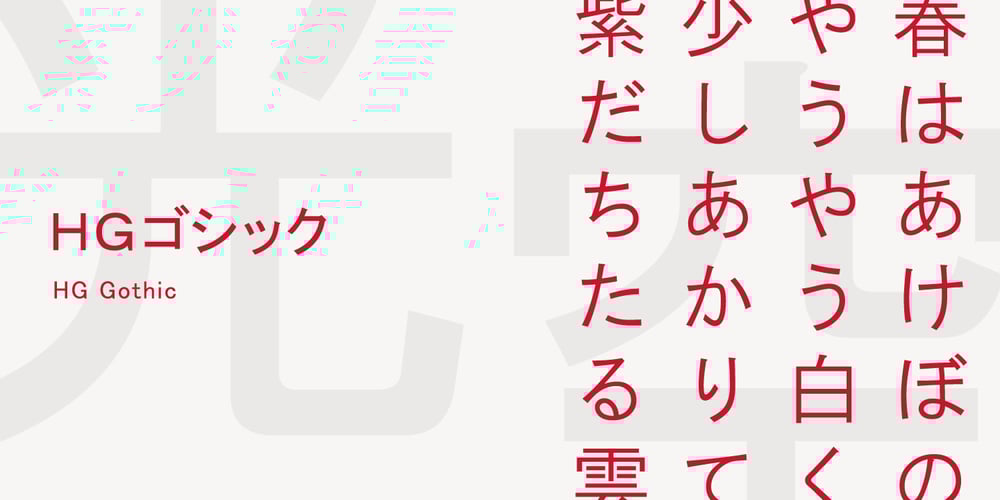
HG Gothic Font Family was designed by published by RICOH. HG Gothic contains 3 styles and family package options. HGゴシックは、リョービの書体「ゴシック」を字母として作られたフォントです。クラシックなデザインがほどこされた正統派のゴシック体ですが、仮名は大きめに作られていて、読みやすいです。Bウェイトは、MSゴシックと同じデザインになっています。M、Bは、本文用途に向いていますが、見出しにも合います。M、Bよりも太いEは、よく目立つので、大きく使うことで魅力が発揮できるスタイルです。